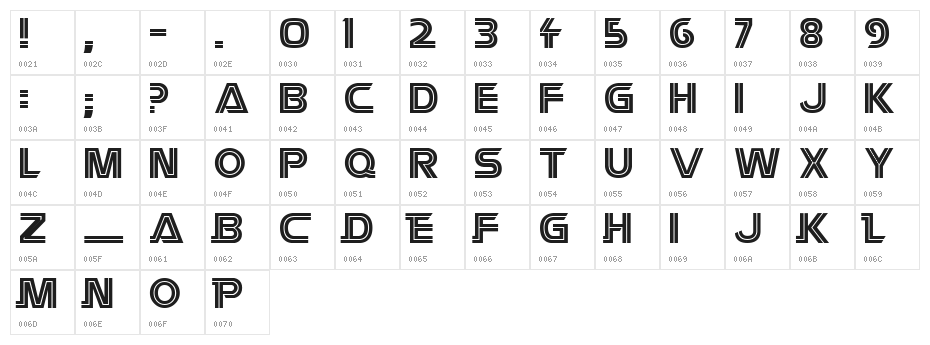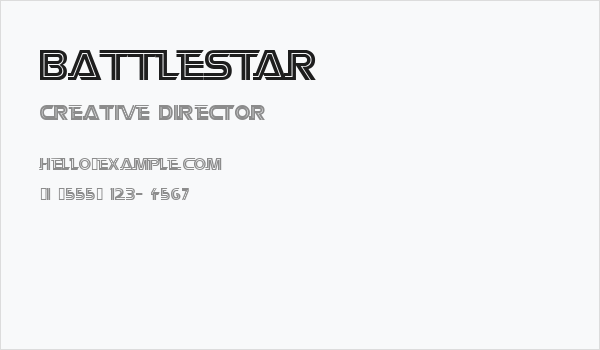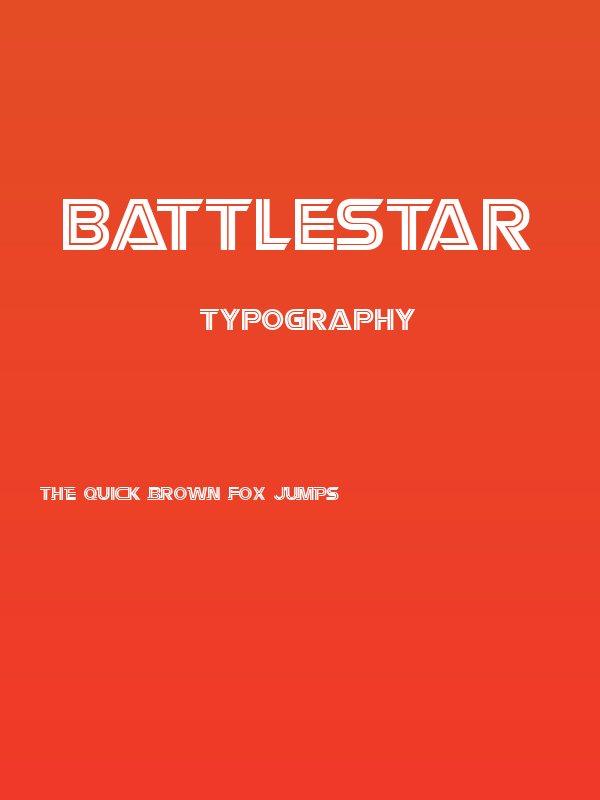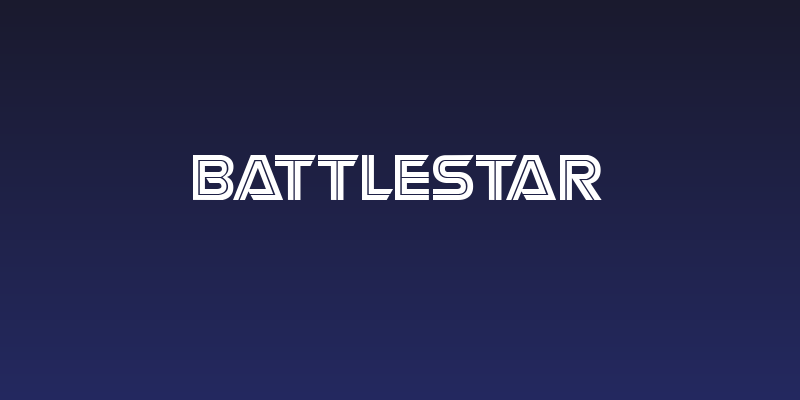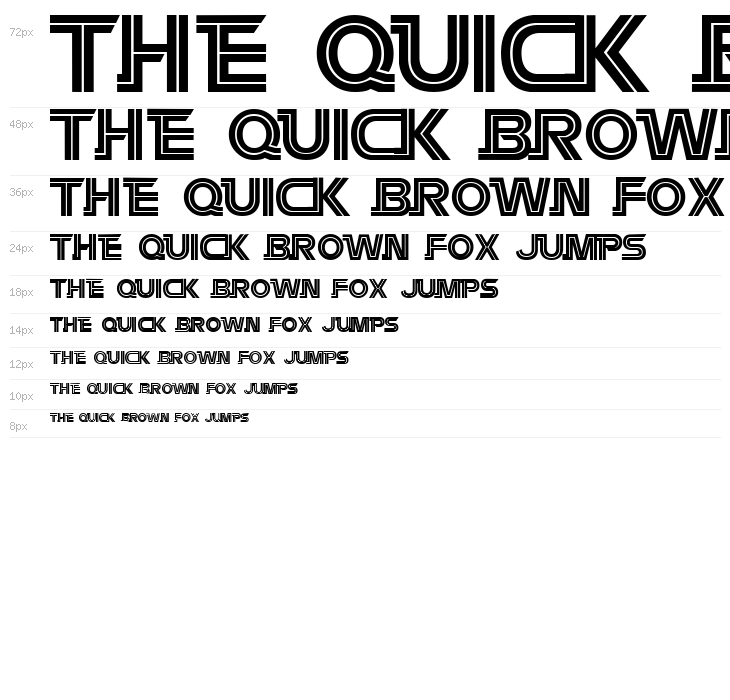
Battlestar Font
| Progetti proposti | Ideal for sci-fi themed designs, video game titles, movie posters, and branding that requires a modern, edgy look. |